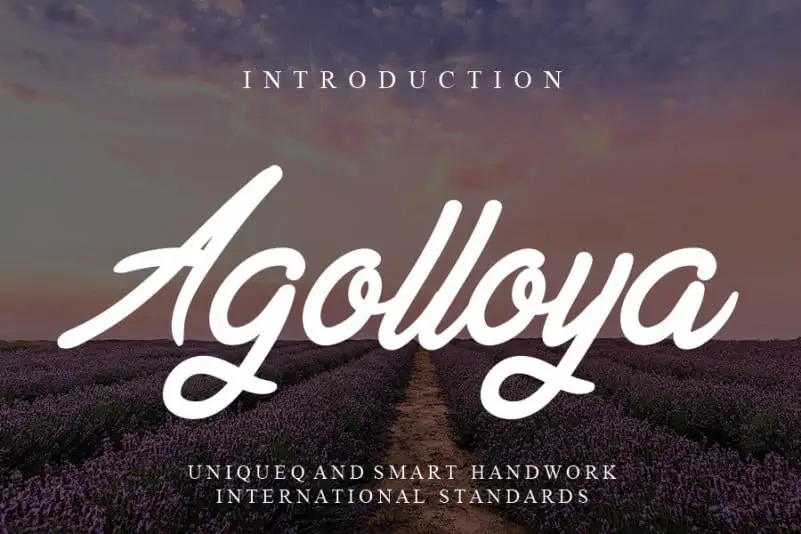
A Agolloya Handwritten Font é uma face tipográfica elegante que preserva influências manuscritas serifadas ao mesmo tempo que se mantém atual e fresca. Suas linhas delicadas e características distintivas trazem um toque romântico à sua escrita, ideal para uma variedade de projetos criativos. Perfeito tanto para estilos mais formais como para trabalhos contemporâneos, essa fonte é perfeita para letras em cartão ou títulos, bem como para embalagens personalizadas e papéis de encomenda. Seja você um designer que busca uma cara diferente na sua próxima campanha ou alguém procurando algo moderno para revolucionar seus materiais impressos, a Agolloya Handwritten Font é definitivamente o tipo certo para seu projeto.